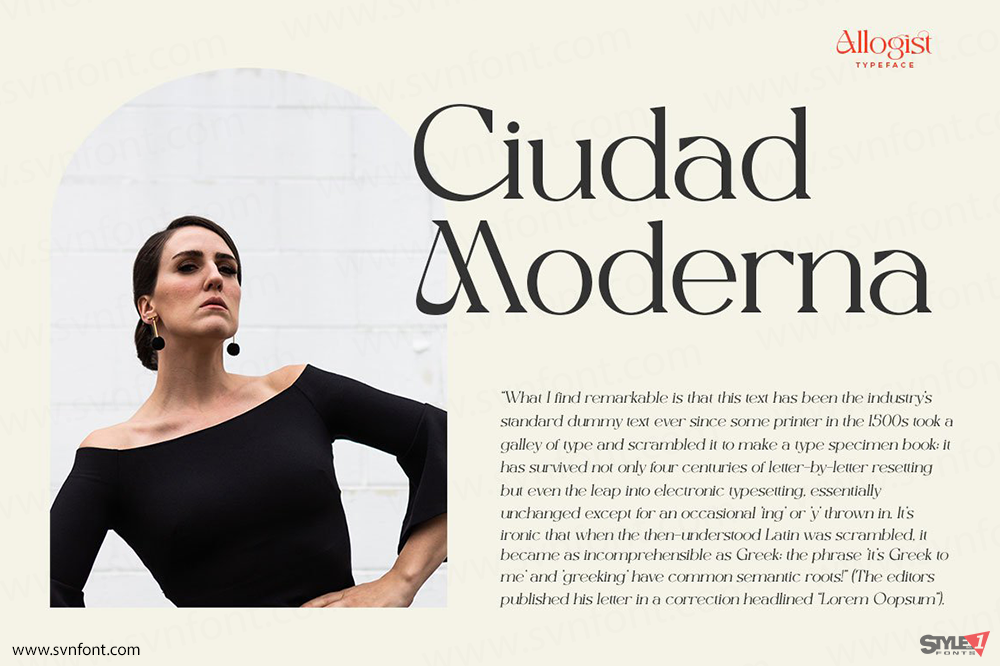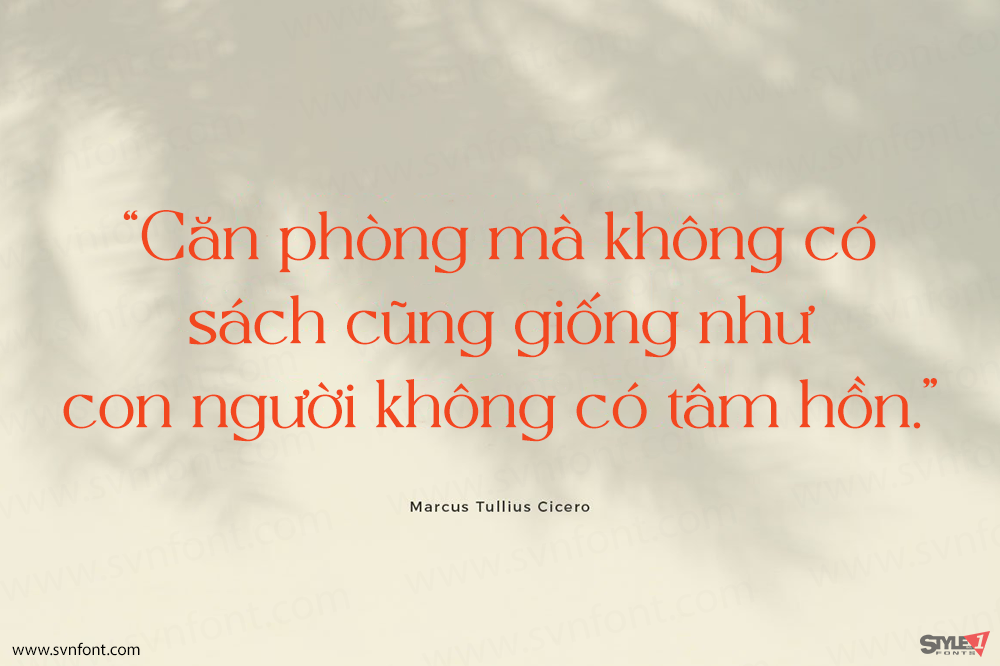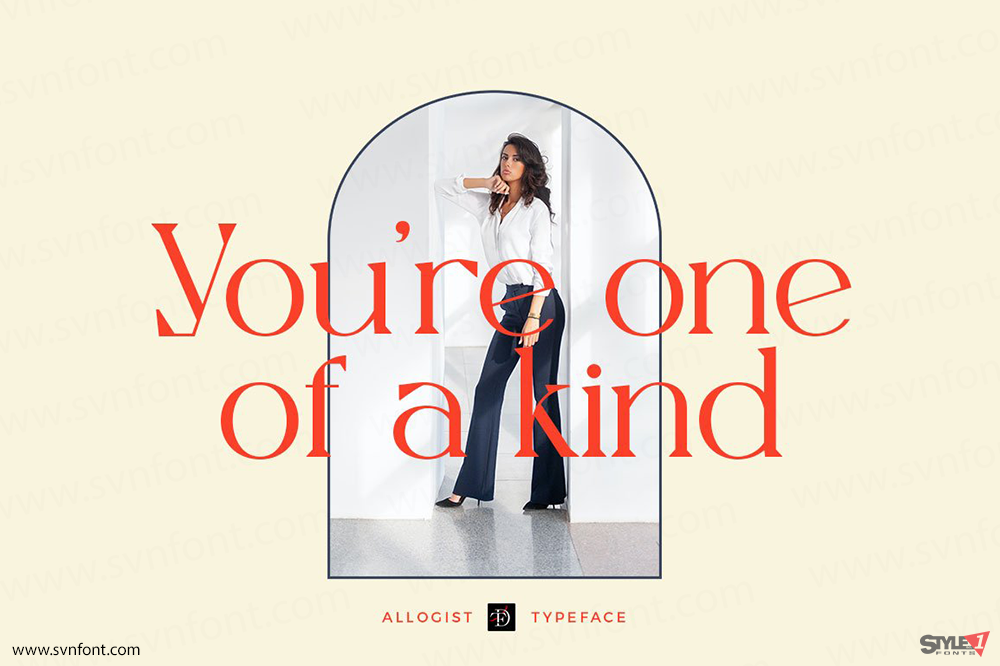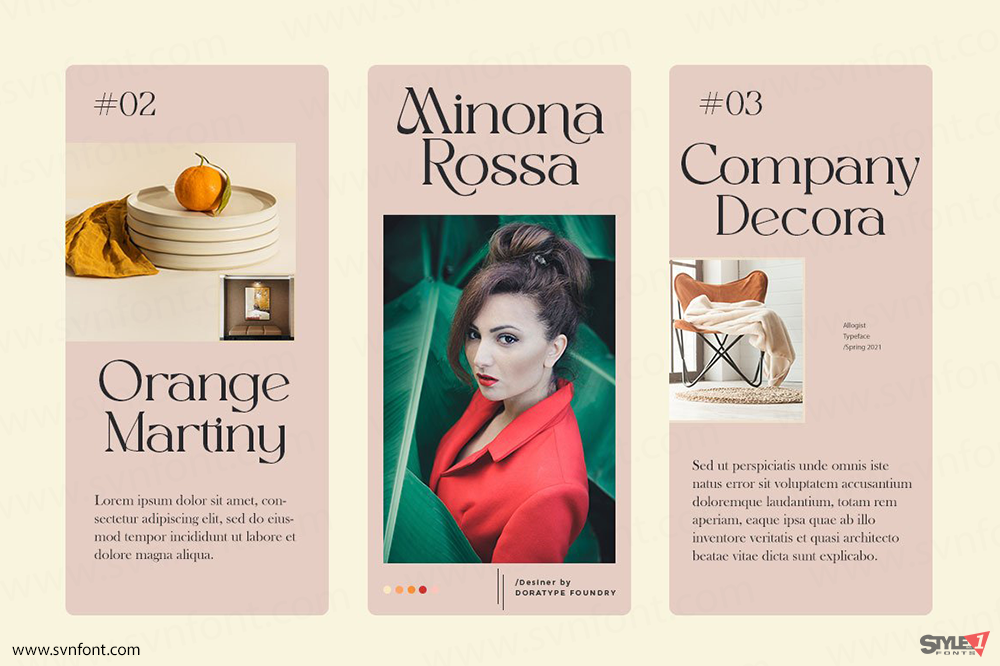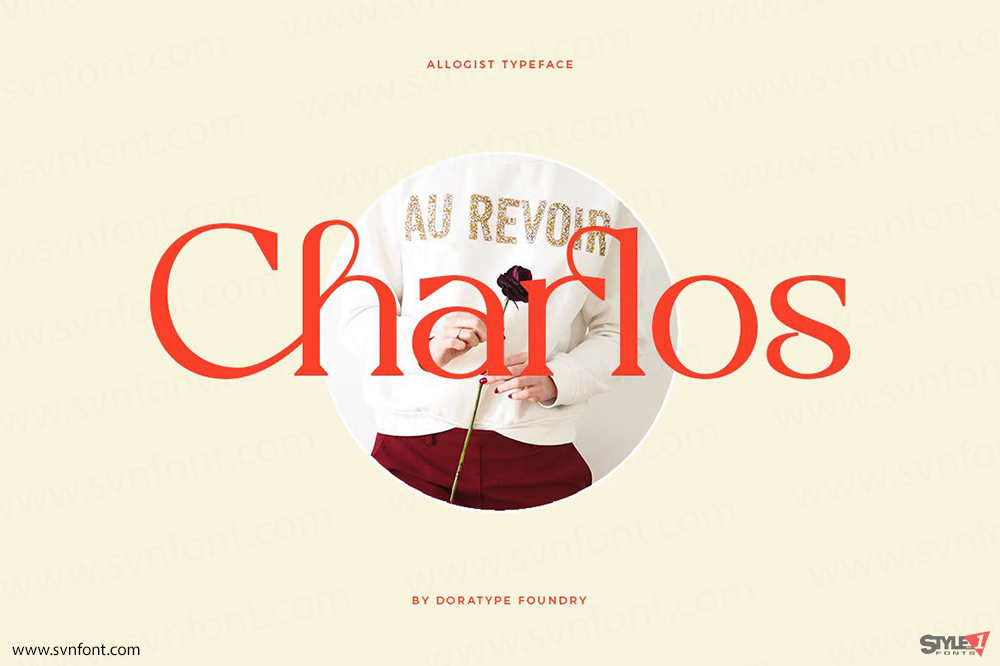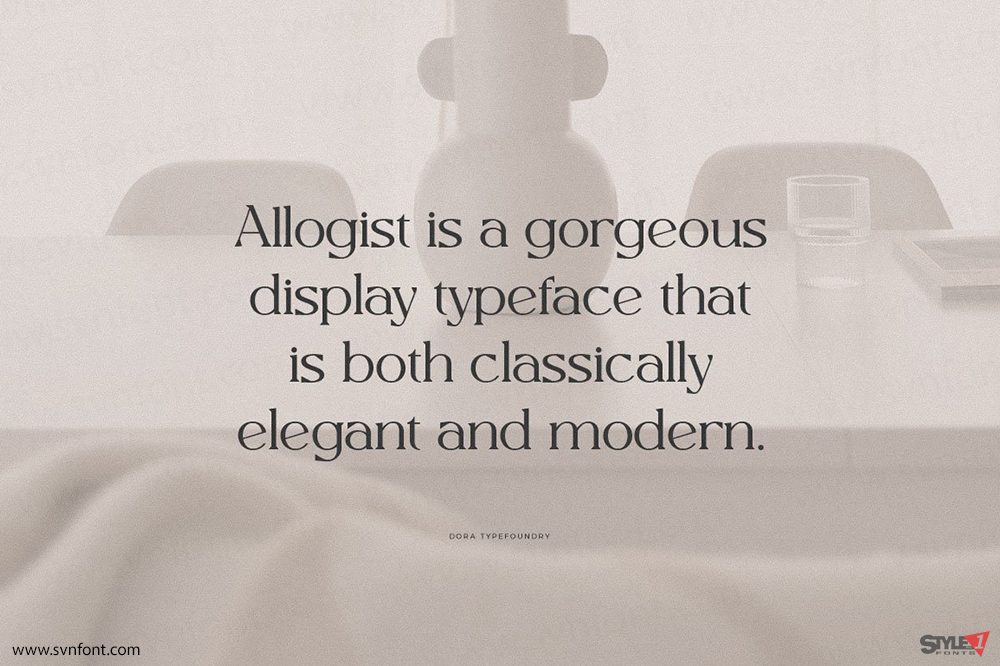
Giới thiệu Allogist — một font serif thanh lịch mới, mang đến cảm giác sang trọng với các chấm kim cương sắc nét, tạo nên phong cách Ba Tư tinh tế nhưng vẫn dễ đọc. Đây là một font đa dụng, rất phù hợp cho dự án editorial, tiêu đề tạp chí, thiết kế logo, branding thời trang, bao bì sản phẩm, đồng thời thể hiện hài hòa cả nét nam tính lẫn nữ tính trong thiết kế.
Nhà thiết kế: Dora Typefoundry
Nhà phát hành: Dora Typefoundry